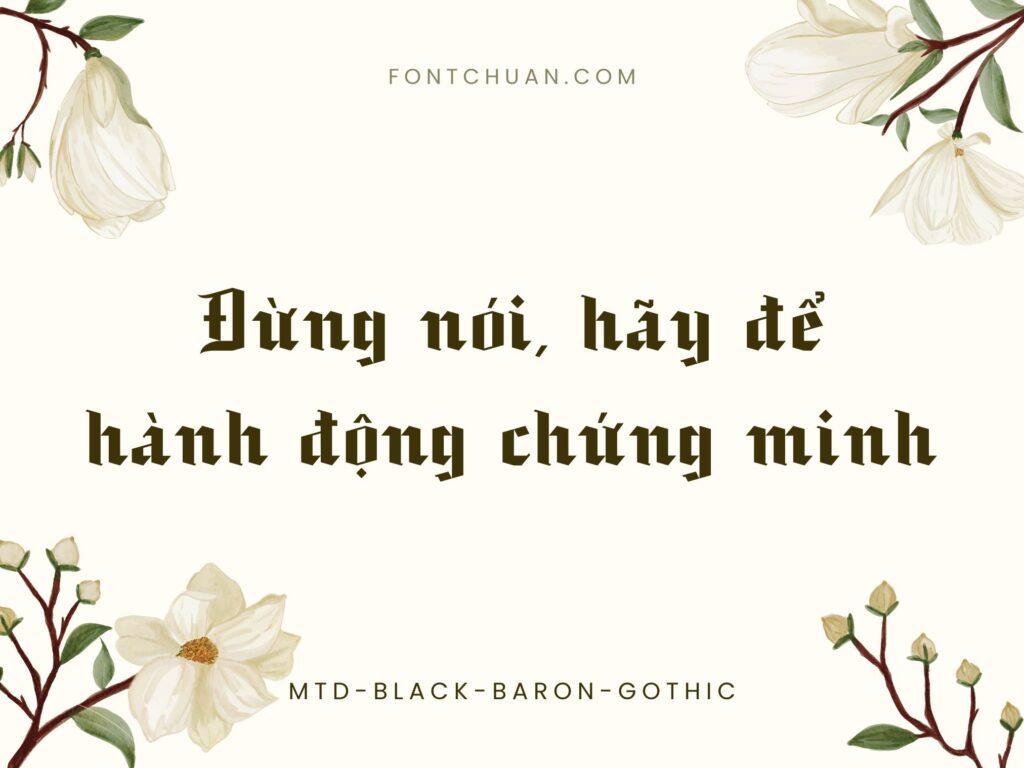
Font MTD Black Baron Gothic Việt Hóa
Black Baron Gothic là một font chữ hiện đại lấy cảm hứng từ các kiểu Font Gothic truyền thống. Với thiết kế đậm nét và các yếu tố trang trí tinh tế, font này mang lại cảm giác mạnh mẽ và cổ điển cho các dự án thiết kế. Để hỗ trợ cộng đồng thiết kế Việt Nam, Mộc Hạ đã Việt hóa font Black Baron Gothic, giúp font này hỗ trợ đầy đủ tiếng Việt cùng hơn 200 ngôn ngữ khác. Phiên bản Black Baron Gothic Việt hóa đã được thành viên Font Chuẩn sưu tầm và đăng tải, nhằm mang đến sự lựa chọn phong phú hơn cho các nhà thiết kế.
Nhờ phong cách Gothic đặc trưng, Black Baron Gothic cũng có thể được sử dụng như một Font chữ Halloween, giúp tạo nên không khí huyền bí, cổ điển và đầy ấn tượng cho các ấn phẩm sự kiện, poster hoặc tiêu đề chủ đề lễ hội.
Về đặc điểm thiết kế, Black Baron Gothic sở hữu các ký tự với nét dày, góc cạnh và các đường nét sắc sảo, tạo nên sự ấn tượng mạnh mẽ. Font này rất phù hợp cho các thiết kế liên quan đến tiêu đề, poster, logo, bao bì sản phẩm và các dự án sáng tạo khác. Ngoài ra, Black Baron Gothic cũng là một lựa chọn lý tưởng cho các ngành nghề như quảng cáo, bất động sản và giáo dục, mang đến phong cách cổ điển và uy nghiêm. Font này cũng rất thích hợp cho các sự kiện như Halloween, Lễ hội và các dịp đặc biệt khác.